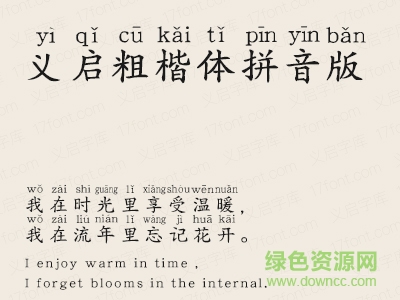
義啟粗楷體拼音版是一款帶有拼音的字體,適合在幼兒教育、學(xué)堂識字的時候使用,方便孩子們記憶,學(xué)習(xí)漢字知識,還等什么,快來綠色資源網(wǎng)踴躍下載使用!
加了拼音的粗楷體,粑粑再也不用擔(dān)心寶寶不認(rèn)識字了。多音字以常用音調(diào)為準(zhǔn),若字體偏小可進入設(shè)置界面調(diào)整大小喔。